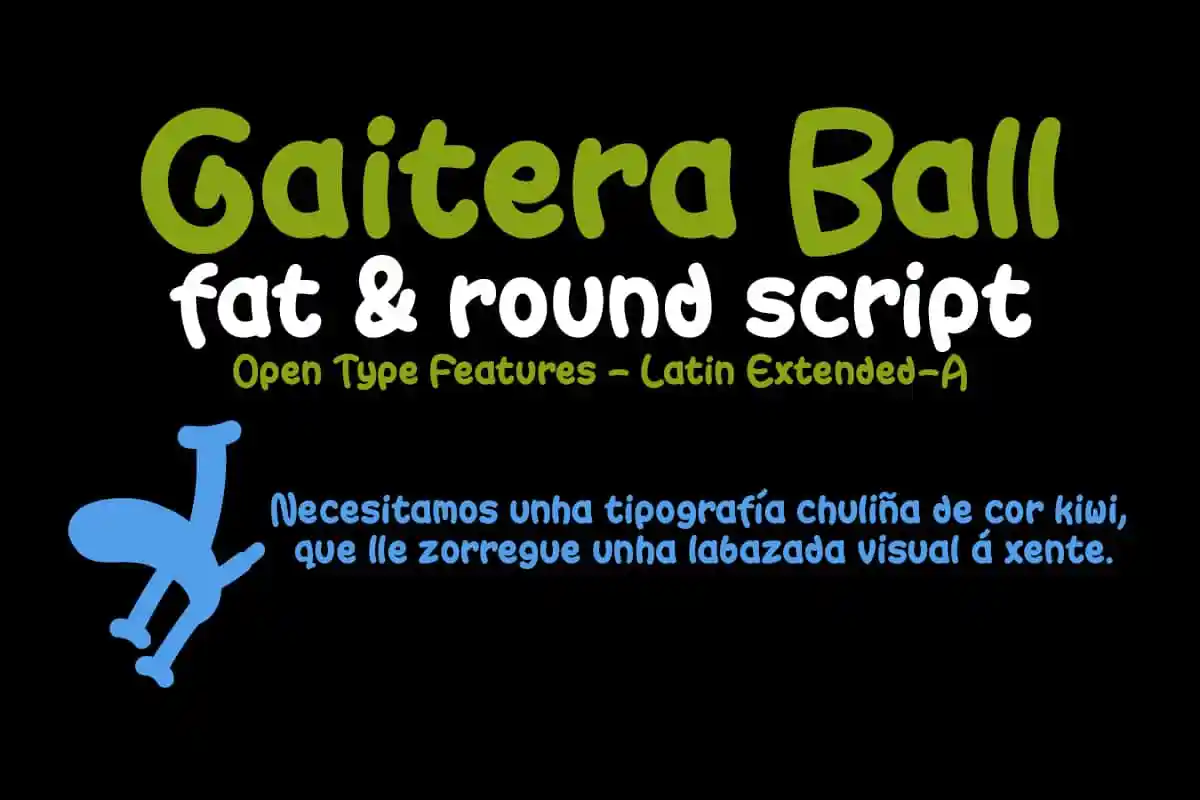
Gaitera Ball Font – Download Grátis
A Gaitera Ball é uma fonte tipográfica feita com um grande pincel esférico usado para escrever a mão. Seu charme e simplicidade a tornam perfeita para criar títulos chamativos, especialmente no estilo de manuscrito. Suas letras maiúsculas em proporção são curvadas e elegantes, dando ao conjunto um aspecto compacto e envolvente. Ideal para designers que buscam uma fonte divertida e versátil para projetos de título, essa font oferece tanto profissionalismo quanto alegria nos seus trabalhos. Com ascenderas e descenders curtos, a Gaitera Ball torna-se ainda mais atraente, ideal para um visual limpo e agradável aos olhos. Foi criada especialmente pelo designer defharo com uma visão deslumbrante para o design visual moderno.